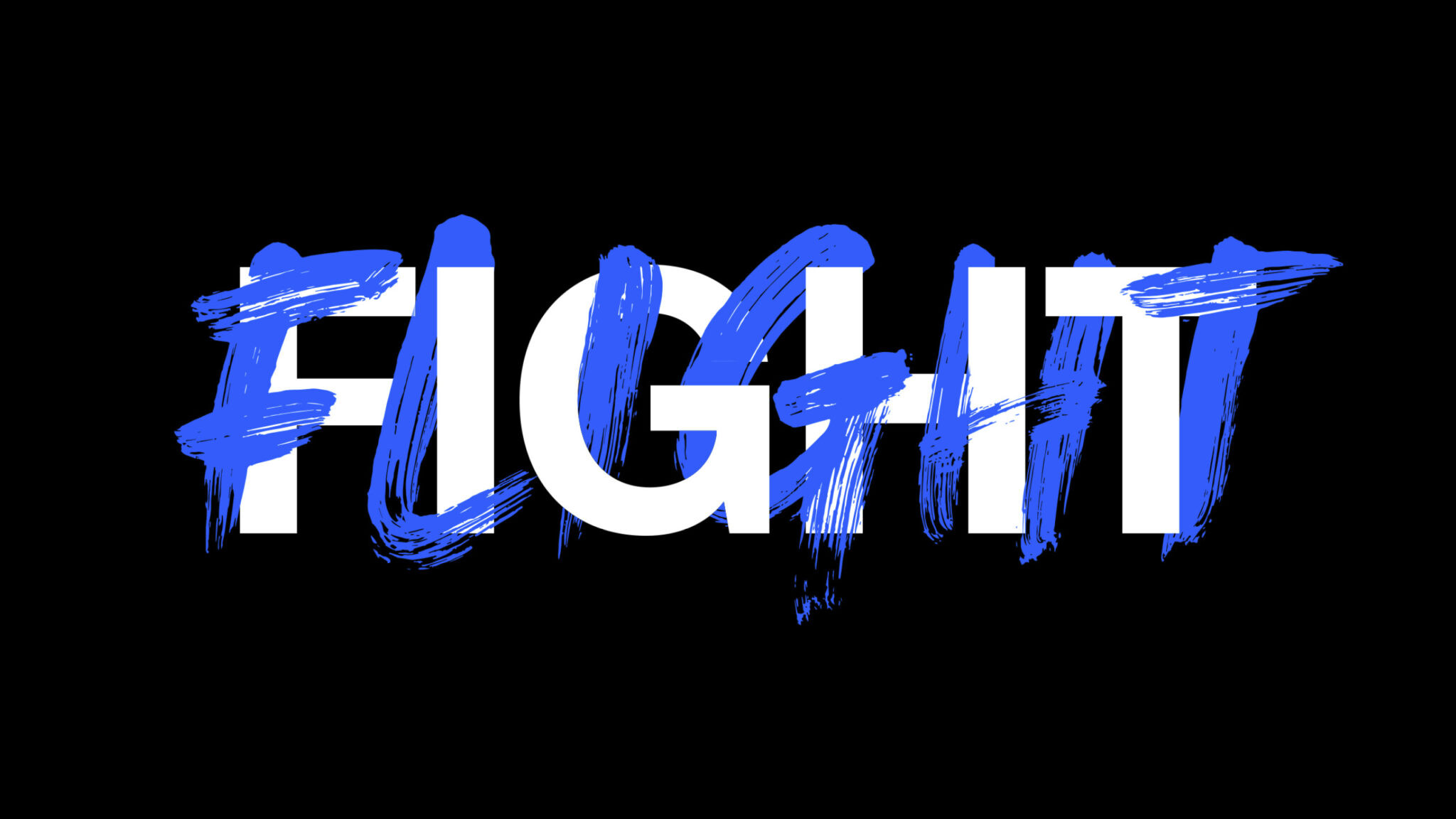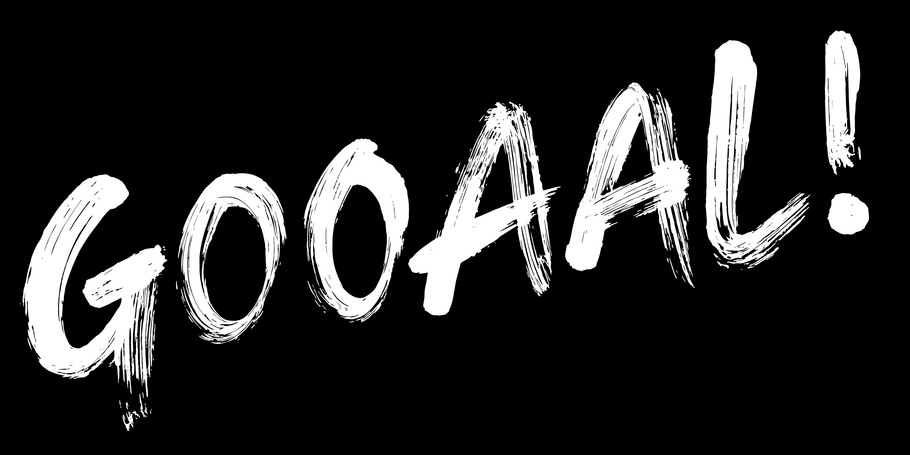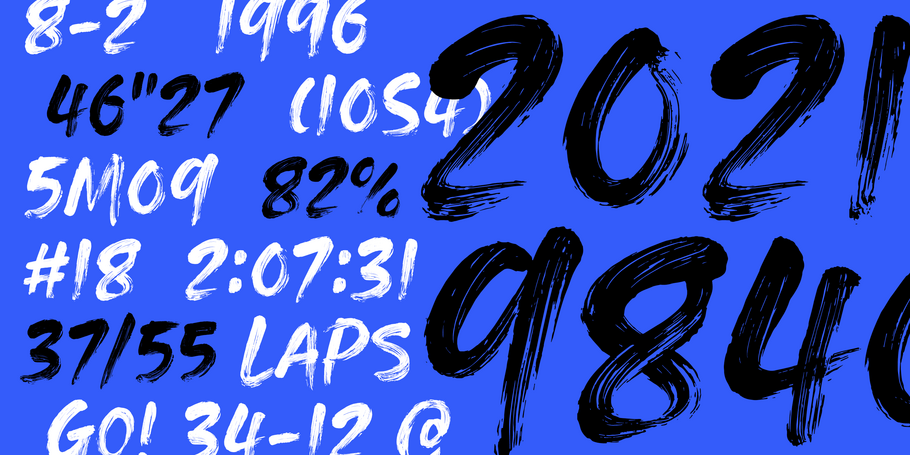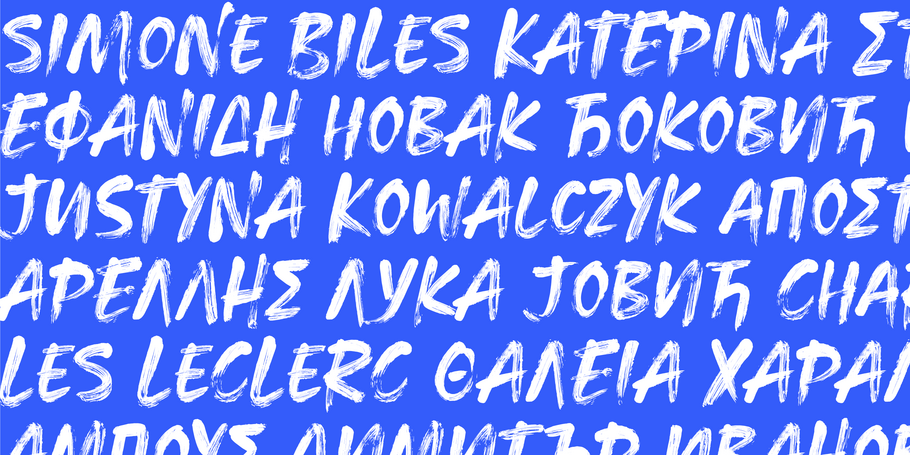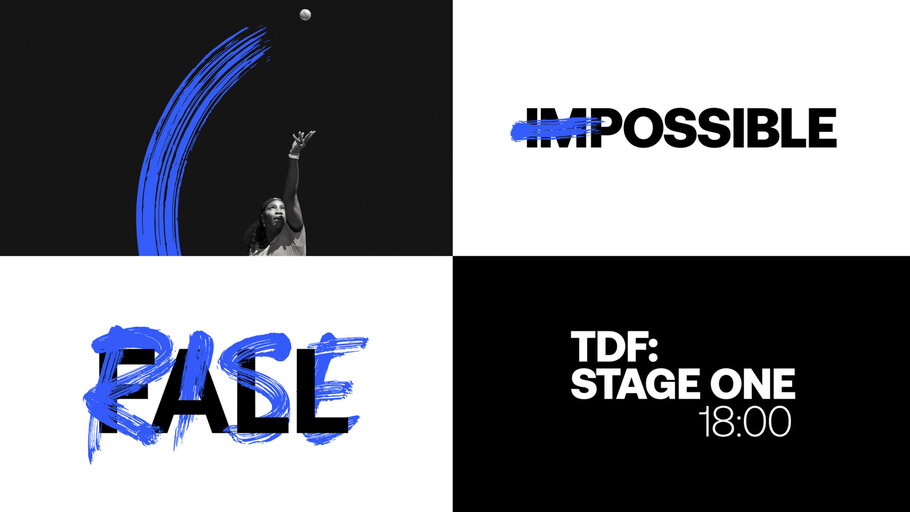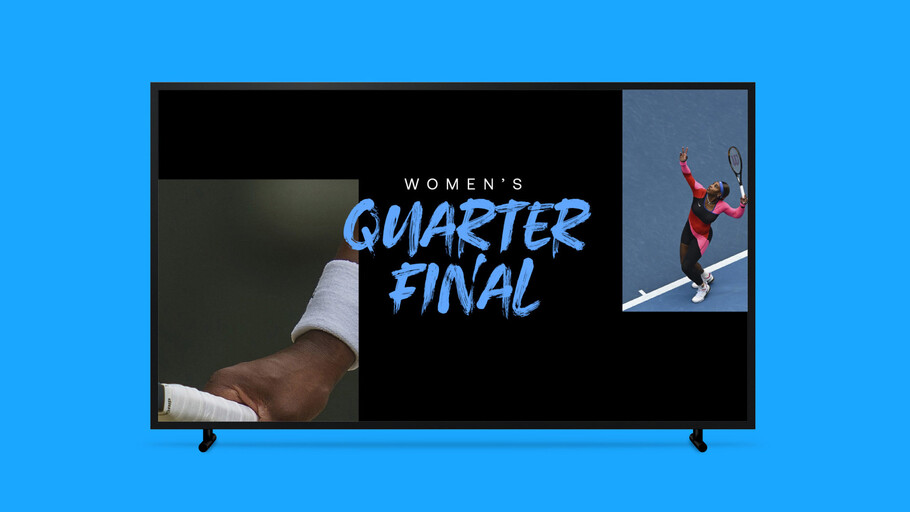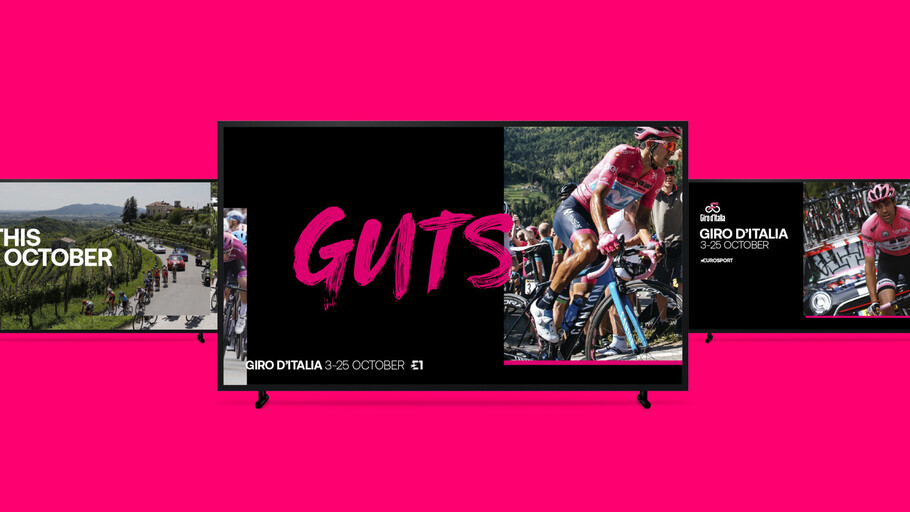
Eurosport RAW
Porter la voix des athlètes et des fans.
Le sport est énergie, le sport est puissance. Le sport est à la fois brut et précis. C’est exactement cela que reflète le rebranding d’Eurosport : la précision et l’énergie des actions sportives. La chaîne de télévision a fait appel à Monotype pour créer Eurosport Raw, une nouvelle police script, énergique et texturée, qui rend la voix de la marque plus éloquente que jamais. Le nouveau système de police Sans et Script révèle la passion pour la performance qui anime la marque Eurosport.
Les nouvelles polices sont comme un équipage de vol pour Eurosport. Elles accompagnent les fans à travers le monde du sport. L’aspect typographique global assure une plus grande cohésion et cohérence sur l’ensemble des canaux et des messages.
« Notre but a toujours été de montrer le sport tel qu’il est vu, aimé et vécu par les fans et les joueurs, [c’est-à-dire] jamais mis en scène ni trafiqué – le vrai sport est vibrant, authentique et narratif, avec un côté brut », explique Dan Capstick, directeur de la création chez DixonBaxi.
« Eurosport Raw est un mouvement rapide et vif, une expression picturale emplie de la vitalité de la compétition. Elle n’est pas décoration, elle est pure action. C’est une police dynamique, créée pour susciter des émotions alignées sur la marque » explique Phil Garnham, directeur de la création typographique chez Monotype.